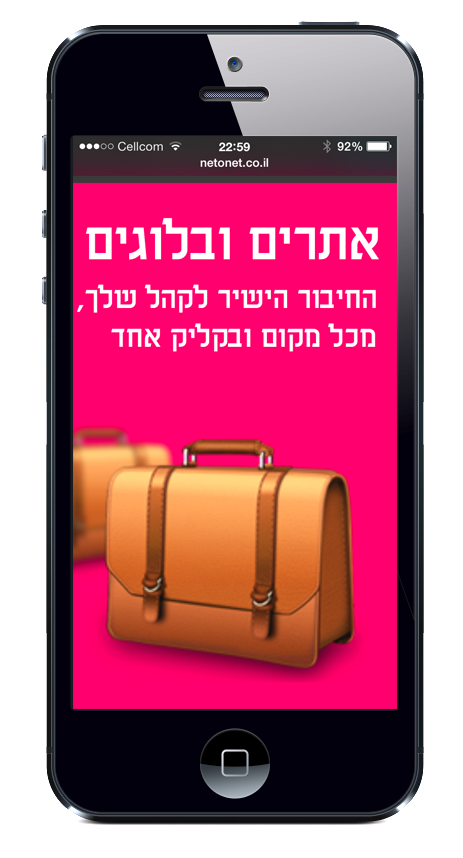
אז למה בעצם צריך פונט מיוחד לאפליקציה?
מאז השימוש הנרחב בסמארטפונים, עולם עיצוב ופיתוח האפליקציות תופס תאוצה וישנה אפליקציה כמעט לכל צורך ולכל מותג.
עד לאחרונה, עולם הפונטים לא שם דגש מיוחד על פיתוח פונטים לאפליקציות, וניתן היה להשתמש באפליקציה רק בפונטים מערכתיים או בתמונות, שהוצגו באפליקציה לעתים באיכות נמוכה וגורעות מחוויית המשתמש.
החדות המדהימה של המסכים מציעה פלטפורמה נפלאה לפונטים מיוחדים לאפליקציות, שזוכות למראה יחודי ורענן עם פונטים שנועדו רק להן. היום ניתן להטמיע את הפונטים שלנו גם באפליקציות, להבטיח בידול ולשמור על איכות הפונט הוקטורי, ששומר על קווים חדים נקיים בכל גודל ורזולוציית מסך (לעומת טשטוש הפיקסלים של פונט המוצג בתמונה).
הפונטים המיוחדים שלנו לאפליקציה עוברים טיפול לצפיה אופטימלית על המסך ומעניקים חווית משתמש יחודית, בכל גודל ובכל רזולוציה של המסך.